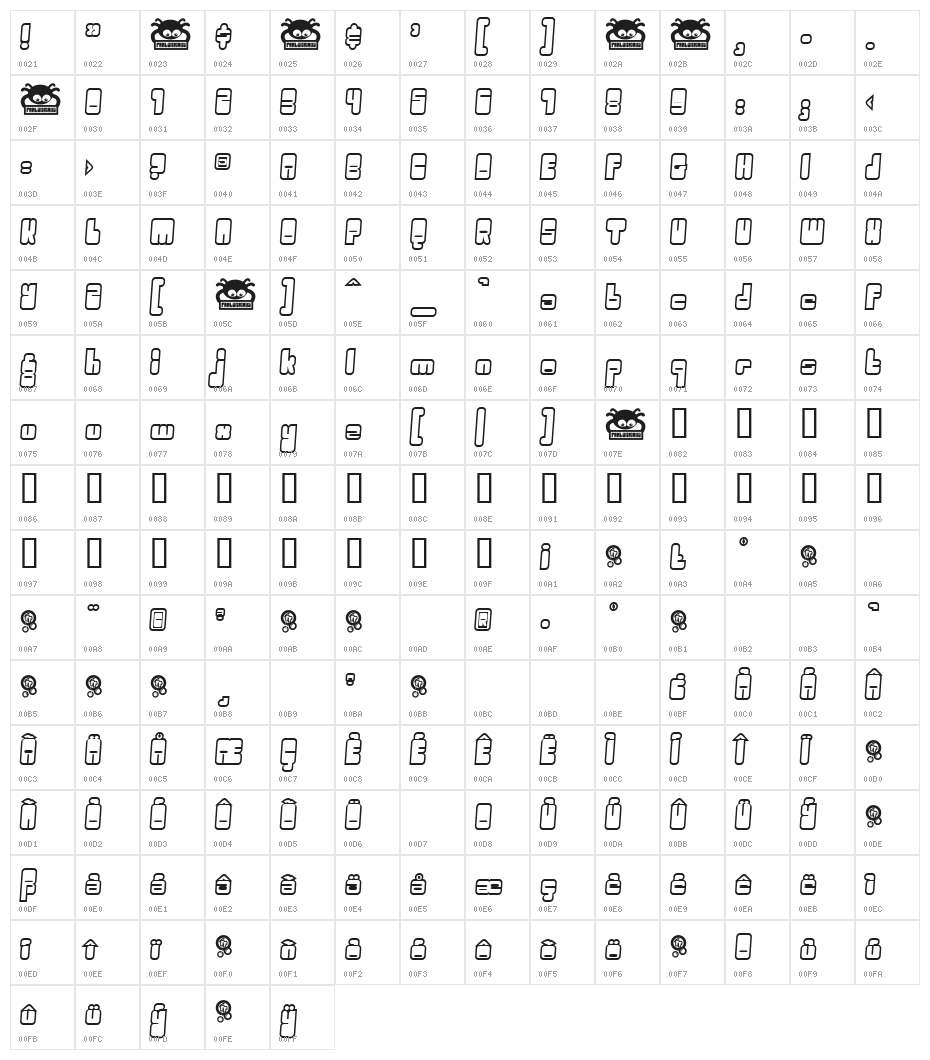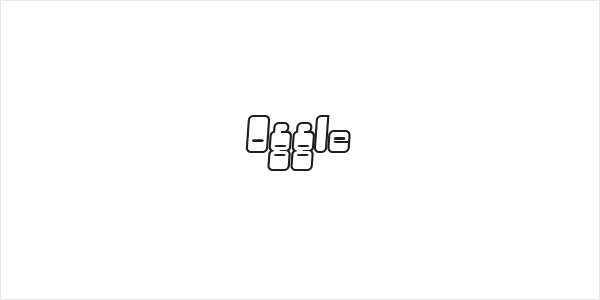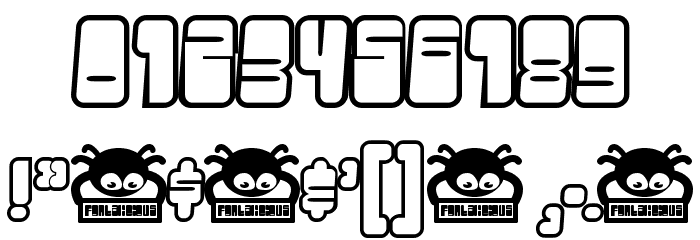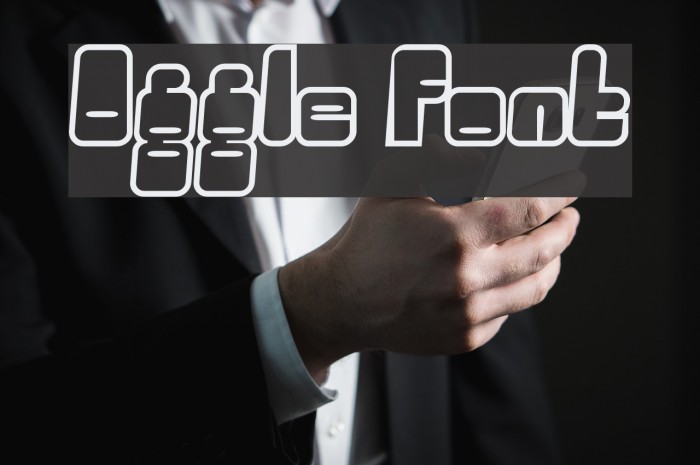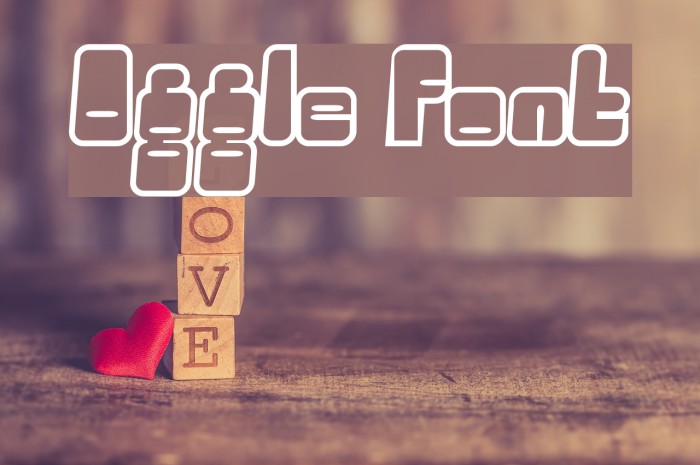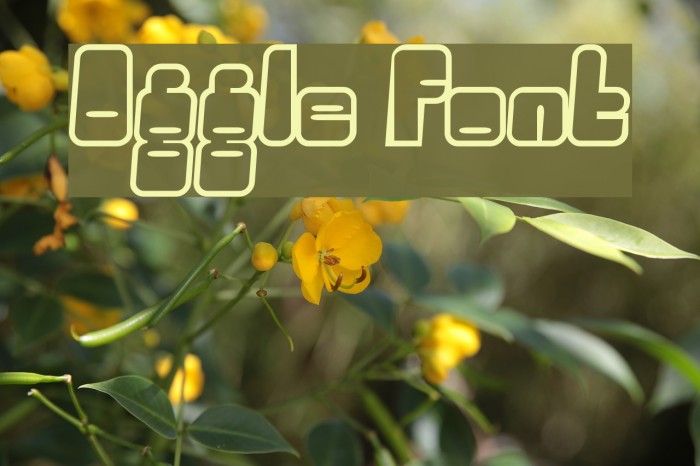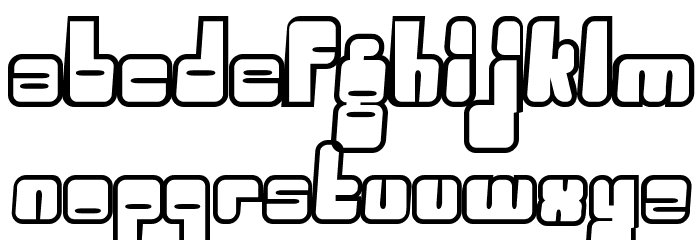
Oggle Font
| समग्र शैली | Playful, Cartoonish |
| उपयोग का मामला | Headlines, Logos, Posters |
| सुझाए गए प्रोजेक्ट | Ideal for children's books, comic strips, playful branding, and party invitations. |